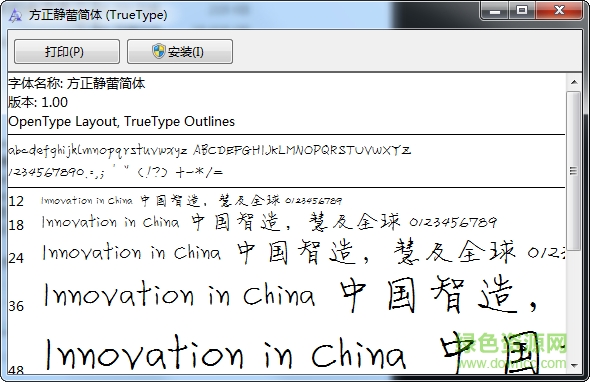
徐靜蕾手寫字體
徐靜蕾手寫字體是一款秀美優(yōu)雅的明星字體,該字體形態(tài)婉轉(zhuǎn),靜中寓動,表現(xiàn)力出色,看上去舒適清爽,十分好看!文章、書刊、海報設(shè)計等領(lǐng)域均可使用!
徐靜蕾手寫體特點(diǎn)
這是一款影視明星徐靜蕾的手寫體。字體骨骼清秀、遒勁有力,清冽而又優(yōu)雅、從容,令人賞心悅目。字如其人,心素如簡,人淡如菊。特別適用于書寫信函、報告、文章等。